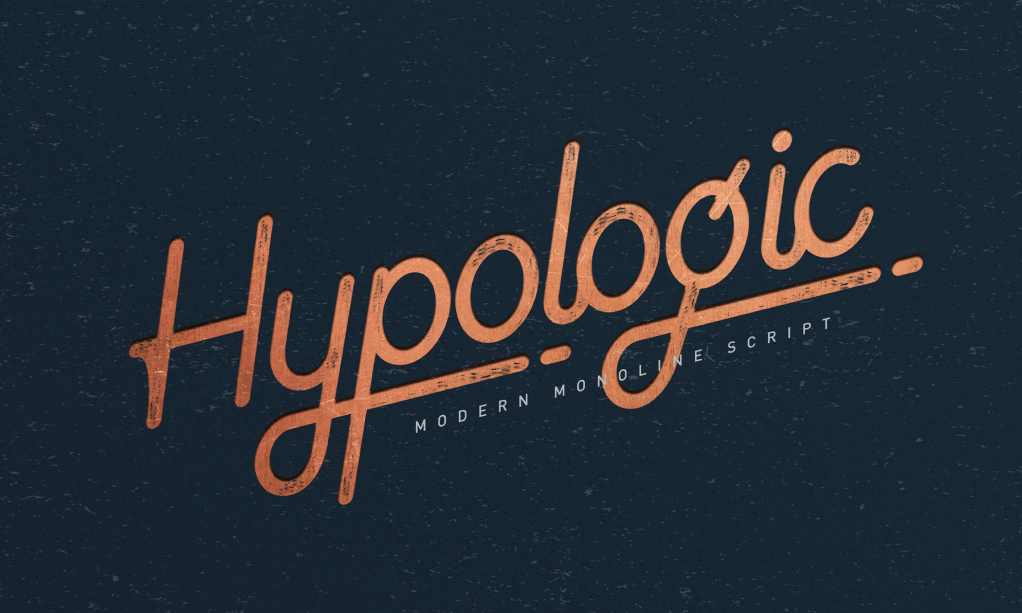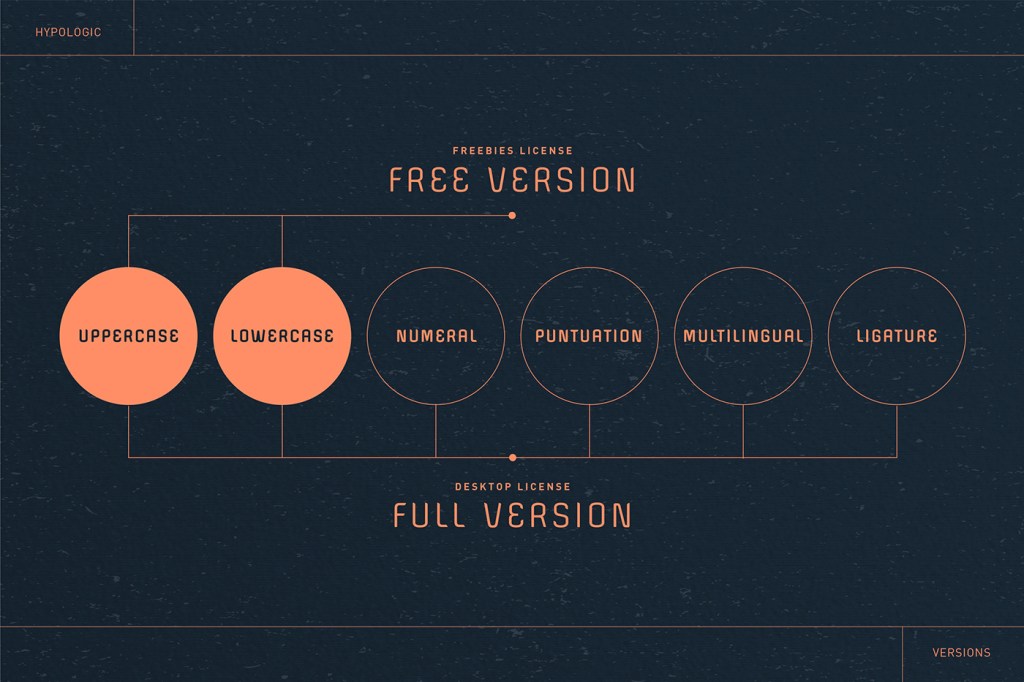
Typographie gratuite : Hypologic de Rocco Angelo
Hypologic est une police monoligne moderne avec des courbes qui rendent cette font très différente des autres polices de script. Cette police d’écriture convient pour différents projets graphiques, de la conception de logo, en passant par la photographie et les œuvres d’art vintage jusqu’aux projets futuristes. Le style de police Regular est disponible gratuitement avec des glyphes limités, sinon un ensemble complet de glyphes et de styles est disponible lors de l’achat de la version complète.